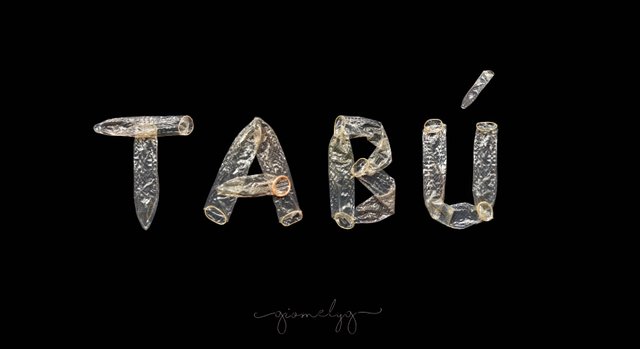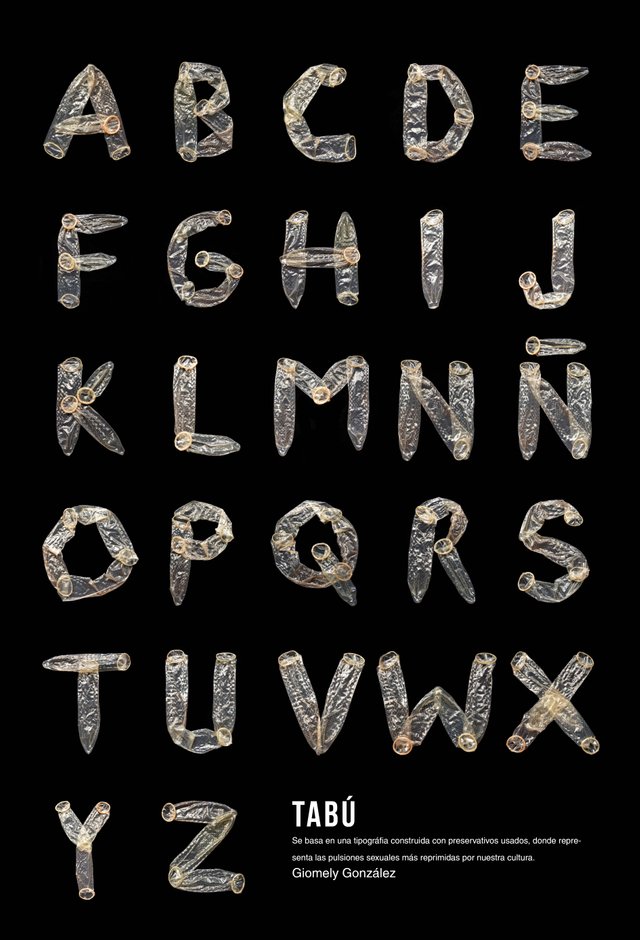
TIPOGRAFÍA EXPERIMENTAL "Tabú"
Esta tipografía experimental fue elaborada por mi, esta construida por preservativos usados en representación de las pulsiones sexuales más reprimidas por la sociedad.
“El hablar de sexo ha dejado de ser tabú, a cambio de que el tabú sea el propio sexo”
-Valerie Tasso
Los prejuicios han logrado reprimir a las personas, preocupandolas sobre lo que está bien y lo que está mal, lo que es correcto e incorrecto. ¿Y quién rayos determina esto? ¿Por qué tanto miedo?
Según Freud, La meta de la pulsión sexual humana es, una ganancia de placer, es decir que la pulsión tiene como meta su propia satisfacción.
Tenemos sexo porque es algo natural, porque queremos, porque nos gusta, porque nos da placer, porque nos satisface y eso es una pulsión sexual.
¿Por qué censurar desnudos, pero no una escena de violencia? La sexualidad es tan natural como respirar, por lo cual este no tiene ser un tabú y la sociedad debería aceptarlo y dejar de ocultarlo, hacer que deje de parecer un fantasma ya que hoy en día está presente desde la música hasta las publicidades, pero siguen escondiéndolo y alarmándose cada vez que aparece.